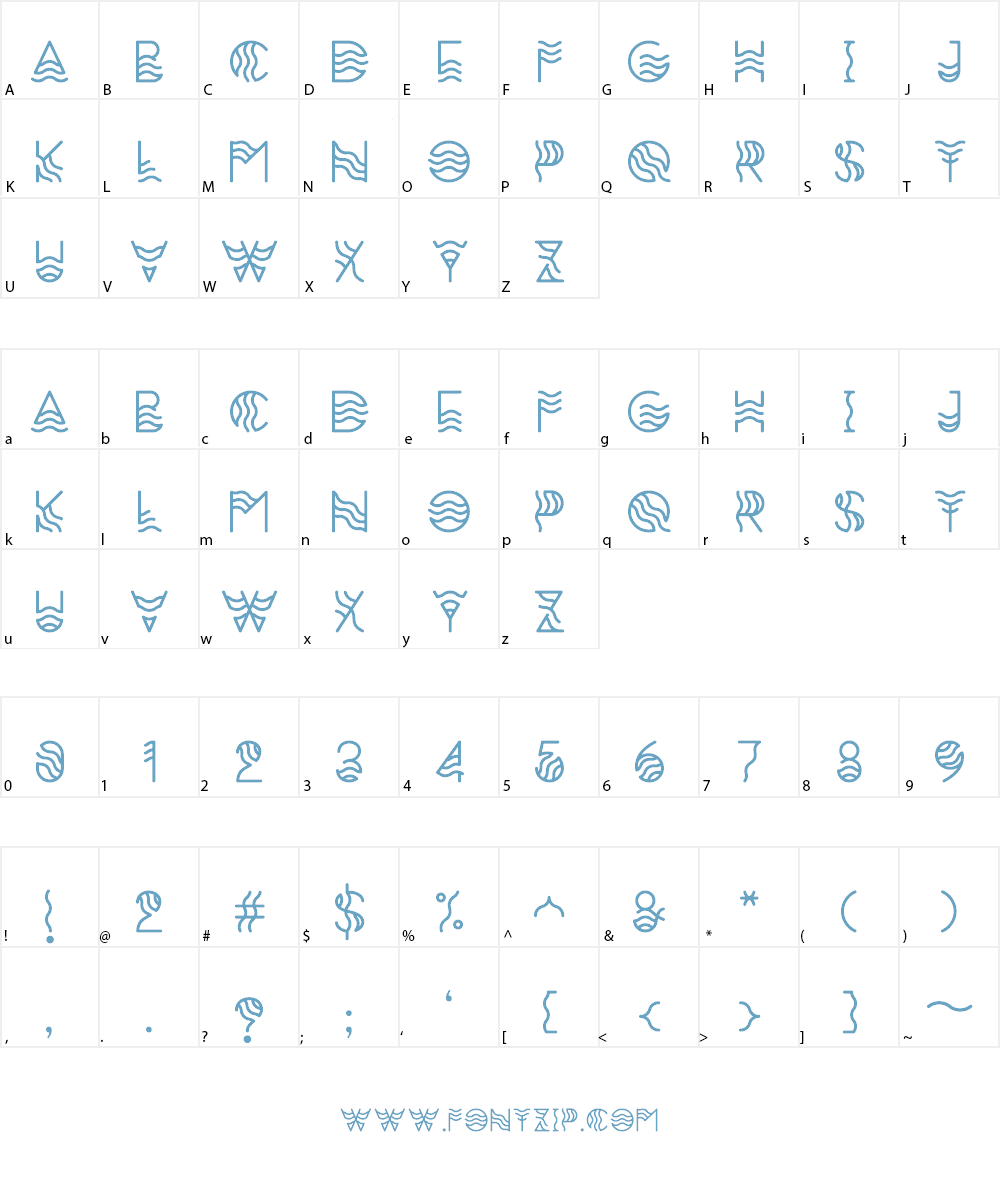
Zilap Marine, nace en un tarde de descanso en las playas de Necoclí “La Perla del Caribe”.
Una tarde de buena música, buen sol y la mejor de las vistas, con esa limpia playa y el inmenso mar de frente, con todo ese paraíso visual me llego la idea de hacer una fuente en representación de nuestro espacio marítimo, especialmente en la Zona de Urabá (Turbo, Necoclí, Arboletes), pero sin dejar por fuera el resto de Colombia.